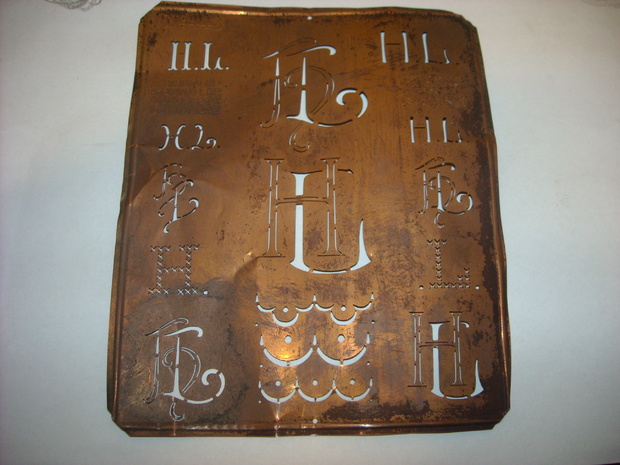
Da fällt mir ein, ich habe doch neulich im Schanzenviertel noch etwas für Euch gesammelt:
Die gi-Ligatur ist ja sehr nett, die Giraffengraphik nicht gerade einladend.
Ich habe die Fotos in Eile im Vorbeigehen gemacht, deshalb kann ich Dir jetzt leider keine Auskunft darüber erteilen, was die in dem Laden genau treiben. Giraffen zünden sie aber – glaube ich … nicht an. :-?
… was die in dem Laden genau treiben. Giraffen zünden sie aber – glaube ich … nicht an. :-?
Wer weiß? girafentoast ist eine Klitsche für Film, web, print.
Könntet ihr euch vorstellen, sowas wirklich in euer Wohnzimmer zu stellen?
Ich hab hier ja (selbstverliebt) Schriftmuster von mir gedruckt und gerahmt, aber das sind eben nur Buchstaben ... Bei diesen Möbeln hab ich den Eindruck, das das weder schöne Buchstaben, noch gute Möbel sind, weil sie eben zwei Formen gleichzeitig sein wollen/sollen/müssen.
Ich finde, das einzige gelungene Stück ist der z-Tisch. Alles andere sieht extrem gewollt aus. Aber in Schwarz wirkt auch das z sehr trutzig – in Weiß sähe es bestimmt schon ganz anders aus. Oder aus einem tollen Holz gefertigt, Nussbaum oder Wenge vielleicht …
Ich hab hier ja (selbstverliebt) Schriftmuster von mir gedruckt und gerahmt
Will ich auch haben. Aber bitte gesetzt aus der Sofa/Canapé! Wie ist da eigentlich der Stand der Dinge? Und was ist aus Malz und Gulasch geworden?
Ich finde, das einzige gelungene Stück ist der z-Tisch.
Ganz Deine Meinung, den Z-Tisch finde ich auch nicht schlecht, und in weiß, gute Idee.
Will ich auch haben. Aber bitte gesetzt aus der Sofa/Canapé! Wie ist da eigentlich der Stand der Dinge? Und was ist aus Malz und Gulasch geworden?
Momentan arbeite ich an einem inzwischen einigermaßen überschaubaren Halb-Auftrags-Projekt (da wird demnächst wohl was kommen), und nebenher fummle ich an einer Malz Light herum, wenn mir mehr nach Grobschlächtigem ist.
Und danach, ja danach ... Canapé in mindestens 4, wenn nicht 8 Schnitten produktionsfertig aufbereiten. (Einen verbindlichen Zeitplan dazu schaff ich aber nicht, weil ich ganz nebenher irgendwann 2011/12 noch ein Haus kaufen und renovieren will ...).
Gulasch & Co machen momentan Pause – mehr geht nicht, und man verliert auch den Überblick ...
Dieses Stück Blech habe ich heute beim Ausräumen eines Dachbodens gefunden. Die Aufschriften:
Oben links: № 443
Links: MERKENTHALER’s KUENSTLER AUSSTEUER SCHABLONE
Rechts: DAS VOLLKOMMENSTE FÜR SCHULE u. HAUS SCHUTZMARKE
Es ist eine Schablone, mit der die Vorzeichnung von Monogrammbuchstaben auf Aussteuertextilien vereinfacht wird. Diese Schablonen gab es in allen Kombinationen, und früher war es üblich, das Mädchen nach und nach vielerlei Textilien (Bettwäsche, Handtücher, Servietten, Taschentücher und so weiter) mit dem eigenen Monogramm versahen. Daher weisen sie meist die Inititalen des Mädchennamens auf, nicht die Initialen mit dem Namen der verheirateten Frau. Damals wurde der Name des Ehemannes automatisch Familienname, den selbstverständlich auch die Ehefrau trug. Aber den kannte das Mädchen noch nicht, wenn sie begann, ihre Aussteuerkiste mit eigener Handarbeit zu füllen.